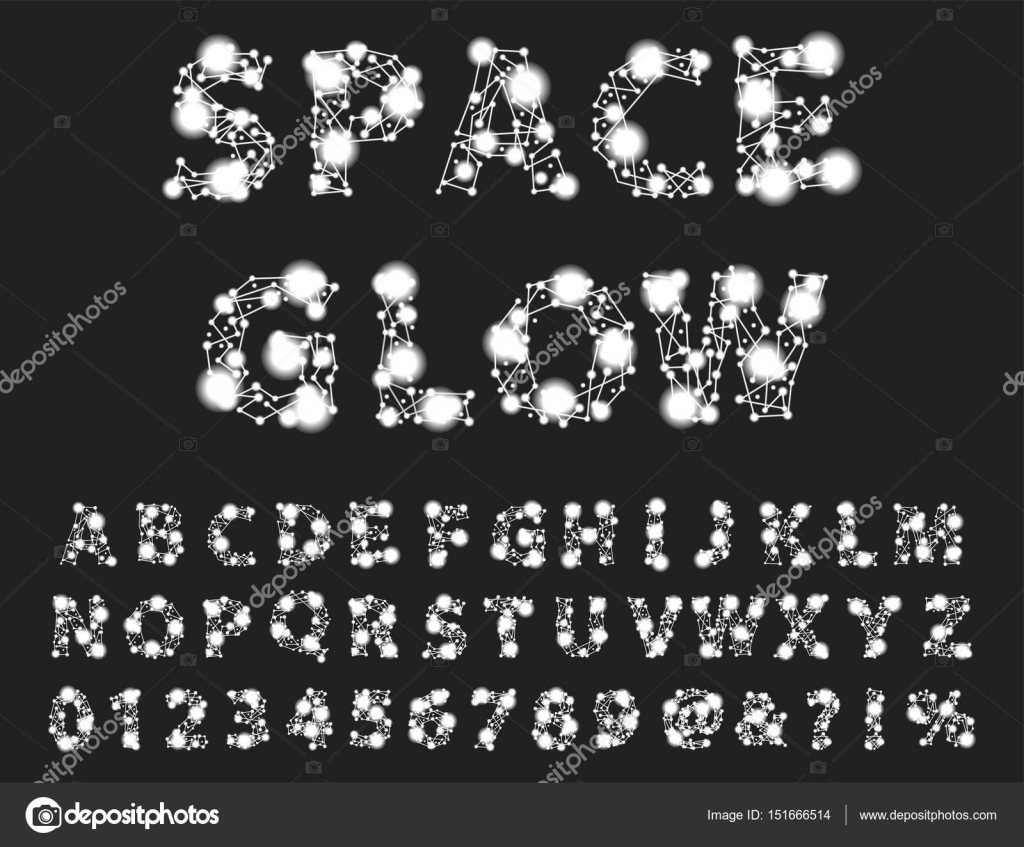
Космические шрифты / Skillbox Media
Шрифты в космическом стиле подходят не только для интерфейсов игр про астронавтов, айдентики частных космических компаний и киноплакатов о межгалактических драмах. Гораздо чаще они нужны, чтобы создать фирменную типографику и логотипы для IT-компаний, технологических стартапов, «мужских» продуктов и научных организаций.
Графика: рисунок шрифта основан на леттеринге логотипа Mission: Space — это интерактивный аттракцион во флоридском Диснейленде.
Кириллица: есть.
Её создал на основе оригинального набора дизайнер под ником Mr.Nobody.
Скриншот: Fonts Online / Skillbox MediaГрафика: геометрические формы букв отдалённо напоминают ар-деко — это визуальная отсылка к типографике плакатов венгерского художника Роберта Берени, которые он делал для табачного бренда Modiano. А острые окончания штрихов, рисунок цифр и буквы S передают образ ретрофантастики.
Кириллица: нет.
Скриншот: Google Fonts / Skillbox MediaГрафика: футуристичный гротеск с угловатыми, но плавными формами и тонкими линиями.
С немецкого языка название переводится как «кончик нитки».
Кириллица: есть.
Изображение: Skillbox MediaГрафика: этот декоративный шрифт — генеративная версия стандартного Rubik. С помощью кода буквам добавили текстуру и рисунок лунных камней.
Кириллица: есть.
Скриншот: Google Fonts / Skillbox MediaГрафика: пиксельно-матричный рисунок отсылает к интерфейсам аркадных игр из 1980-х — или к экранам в рубке космической станции.
Кириллица: есть.
Скриншот: Google Fonts / Skillbox MediaГрафика: за лаконичным, но ярким рисунком шрифта стоит образ Малого Пса. Точки — это будто Процион и Гомеиза, а округлые линии словно соединяют их в созвездие.
Кириллица: есть.
Скриншот: BestFonts / Skillbox MediaГрафика: это шрифт в футуристичном стиле. Он составлен из отдельных резких и плотных линий — это напоминает о трафаретных надписях на бортах космических аппаратов.
Кириллица: нет.
Графика: в рисунке букв явно видна трафаретность, а если вглядеться пристальнее — контраст и высота готики.
Кириллица: нет.
Изображение: Skillbox MediaГрафика: в рисунке букв Cheorcy угадывается одновременно минимализм, ар-деко и стиль космической эры. Например, O напоминает траекторию орбиты.
Кириллица: нет.
Скриншот: Ergibi Studio / Skillbox MediaГрафика: у этого шрифта ретроцифровой дизайн, напоминающий о неоново-зелёных текстах на табло в центрах управления полётами.
Кириллица: нет.
Изображение: Skillbox MediaГрафика: Outer Orbit — «Внешняя орбита» — это «резаный» механистичный шрифт в футуристичном стиле.
Кириллица: нет.
Изображение: FontSpaceГрафика: у этого шрифта характер леттеринга, отсылающего к потёртым трафаретным надписям на военном оборудовании и деревянных ящиках, в которые могли бы собирать образцы породы с других планет.
Кириллица: нет.
Графика: в рисунке букв этого акцидентного шрифта угадывается знаменитый логотип NASA.
Кириллица: нет.
Скриншот: Fonts Online / Skillbox MediaГрафика: дизайн этого модельного шрифта суперминималистичный и при этом элегантный.